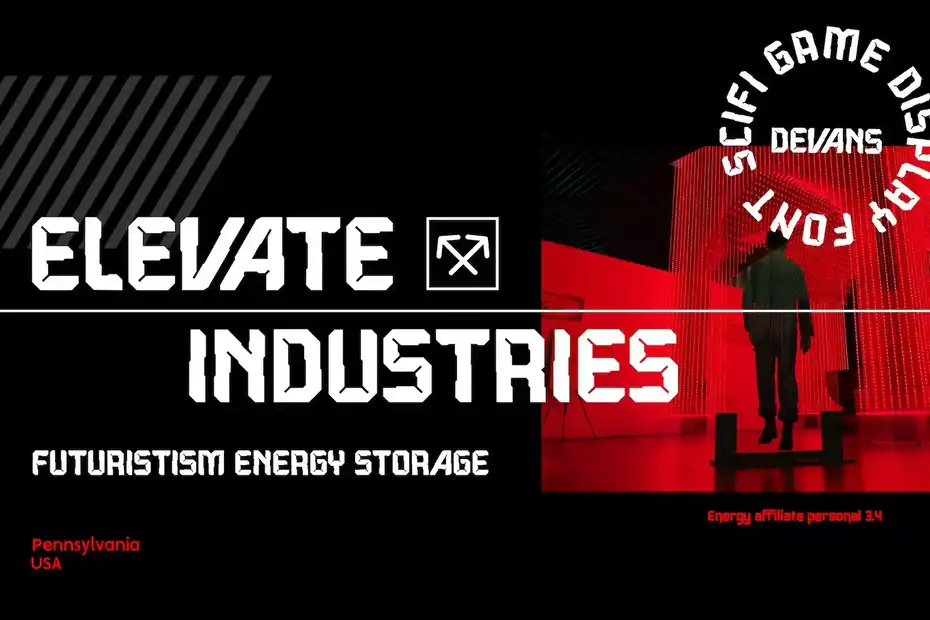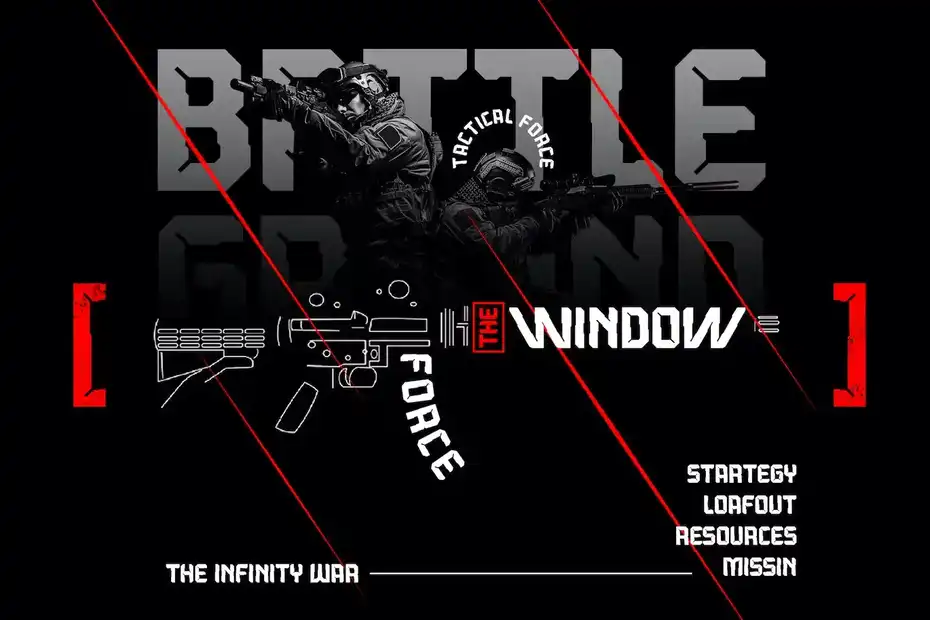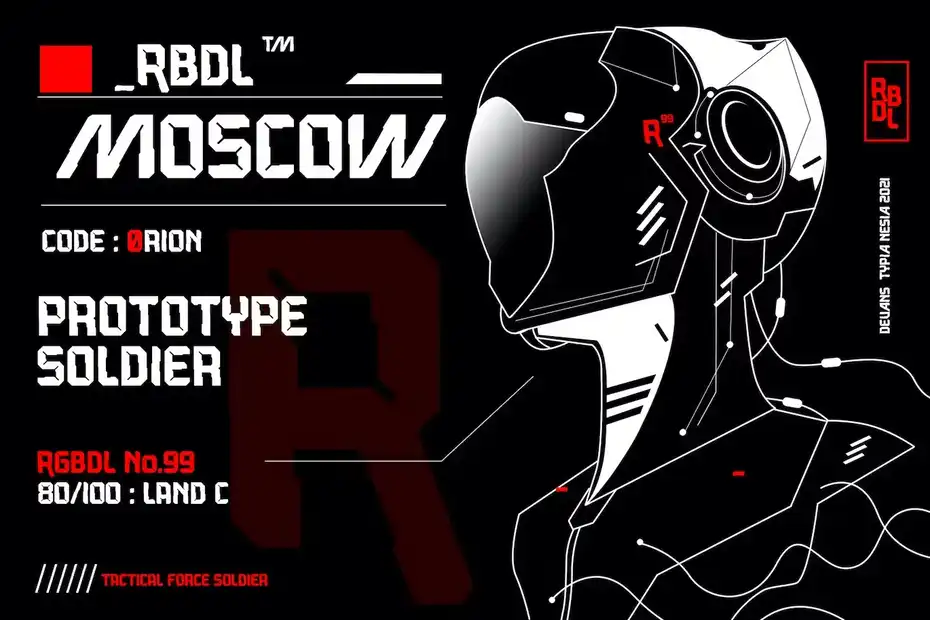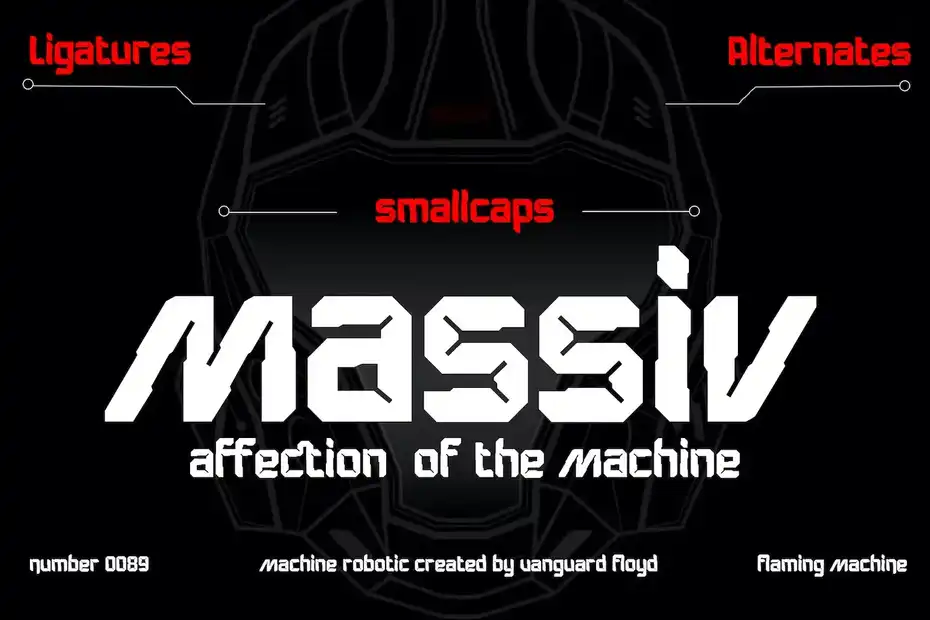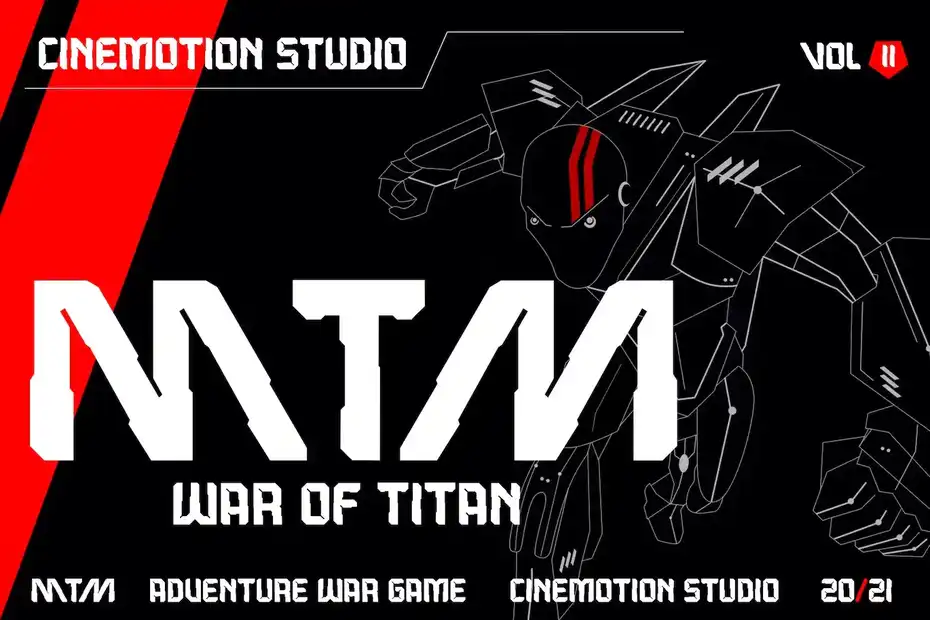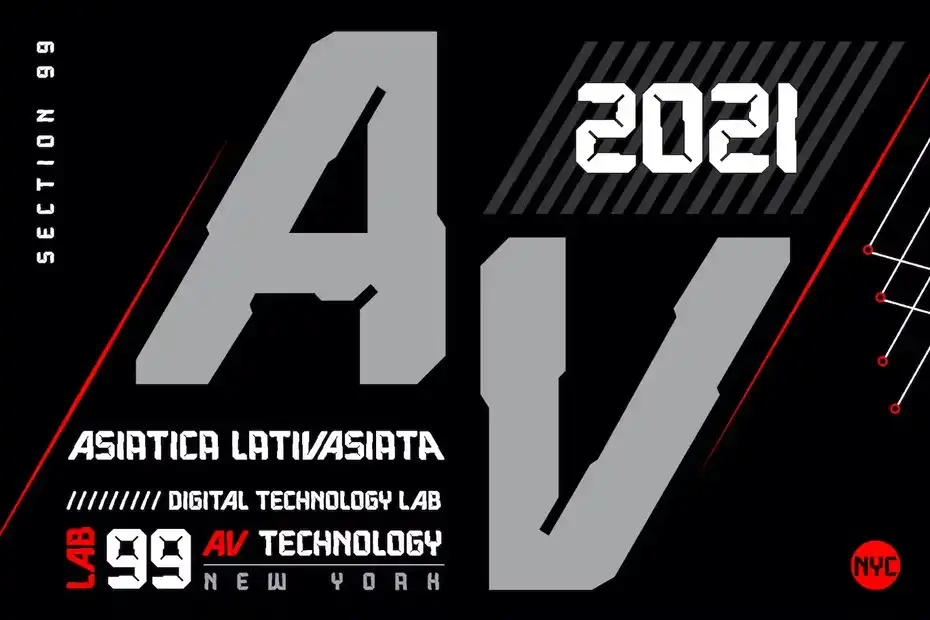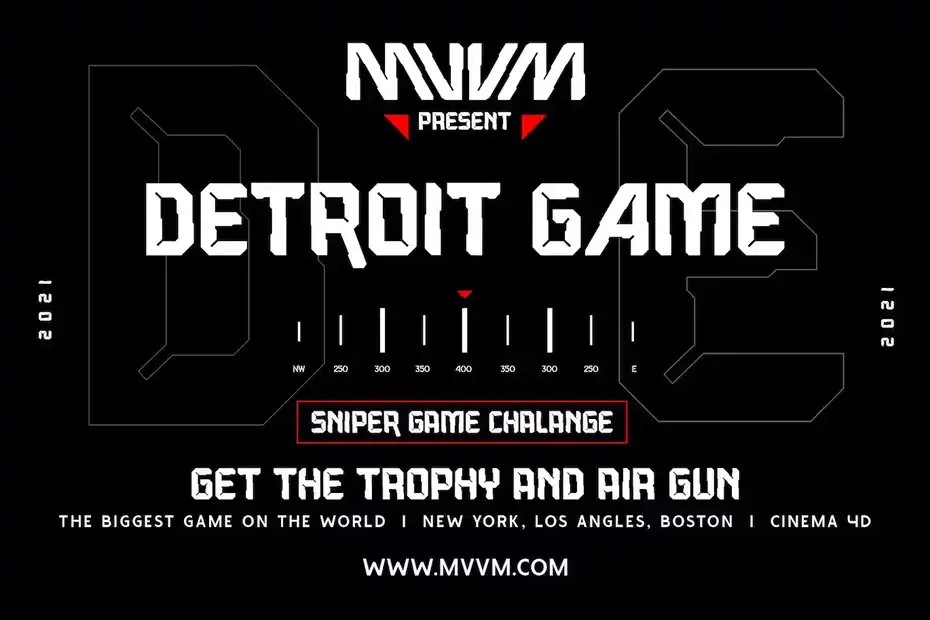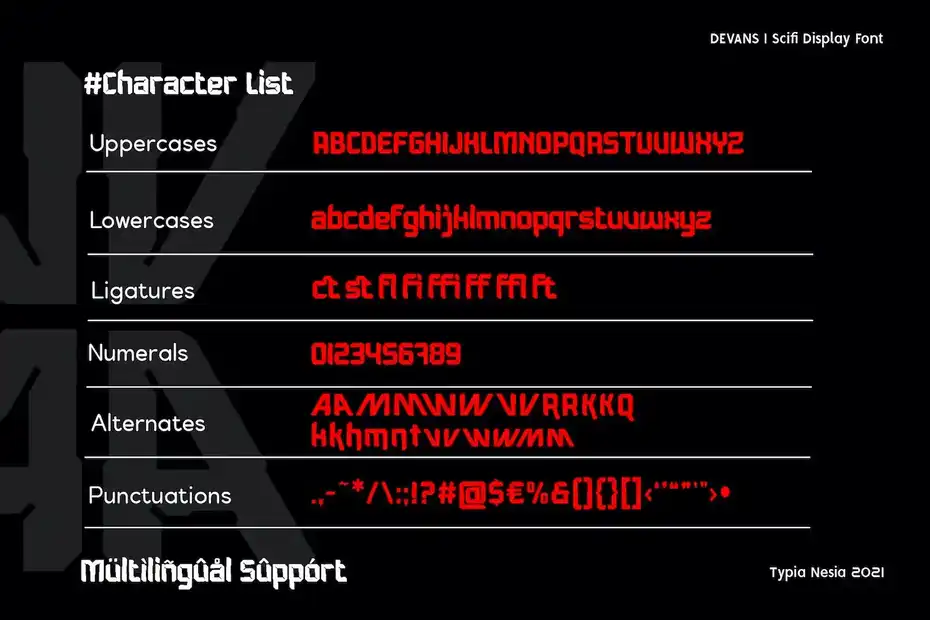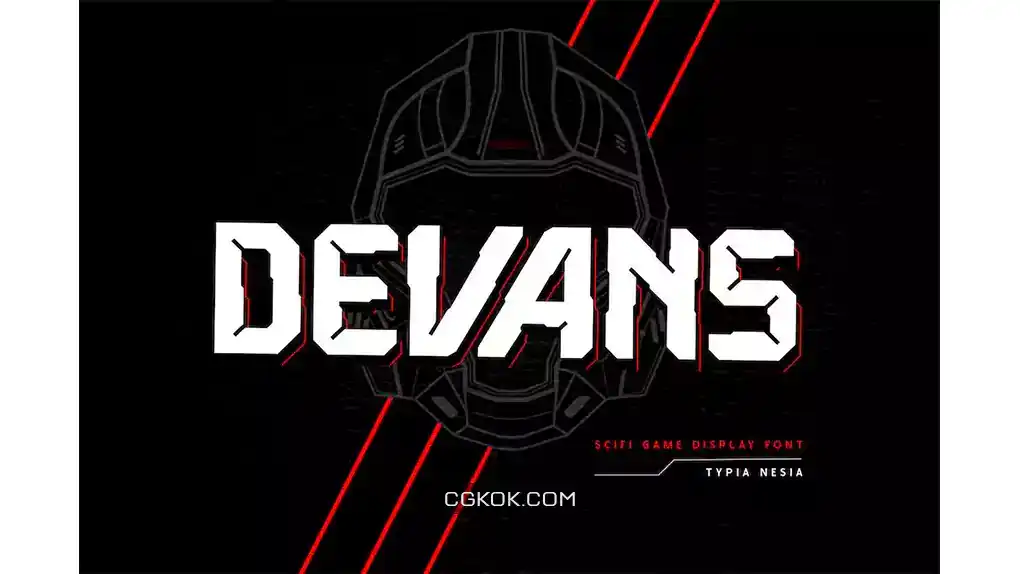
فونت انگلیسی گیمینگ Devans – Scifi Game Font : این مجموعه شامل فونت انگلیسی مدرن است که برای بازی، مسابقه ورزشی، پوستر موسیقی، وبلاگ، تبلیغات مدرن، کارت دعوت، نقل قول، دکوراسیون منزل، عنوان جلد کتاب و غیره مناسب میباشد.
- عنوان مجموعه: Devans – Scifi Game Font
- سبک: Sans-Serif
- فضا بین حروف: معمولی
- اندازه بهینه: بزرگ (نمایش / پوستر)